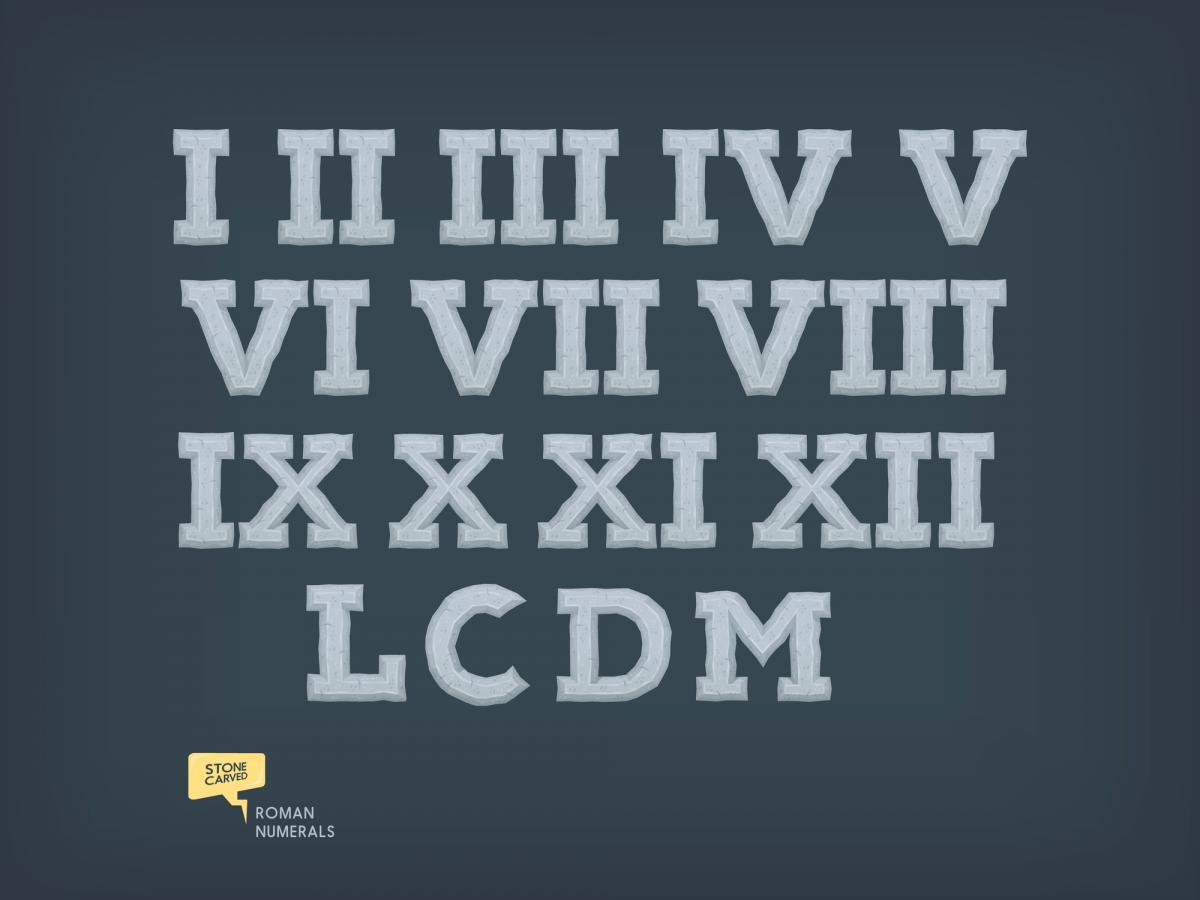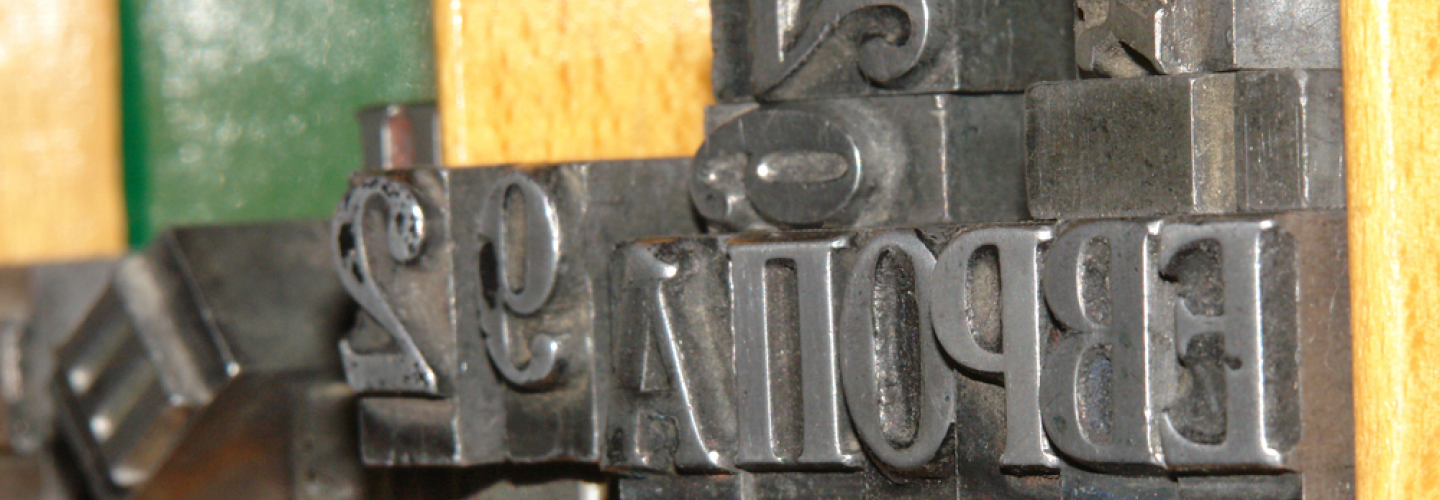
Tipos y características de la tipografía romana
La tipografía romana es una de las más utilizadas y reconocidas en el mundo del diseño gráfico y editorial. Su estructura se caracteriza por la presencia de serifas y por el contraste entre los trazos gruesos y finos, que le permite ser fácilmente legible. Con el paso de los años, han surgido algunas variantes. Todas ellas las conoceremos en detalle en este artículo.
Tipografía romana: principales características
La tipografía romana destaca por su elegancia y legibilidad. Por eso, es tan usada en diseño gráfico y editorial. Su característica principal es la presencia de serifas, que son pequeños trazos que adornan los extremos de las letras. Cuando se trata de un texto largo, son estos los que facilitan la lectura. Pero además, estas serifas le dan un aspecto un tanto clásico y refinado, de ahí que sean habituales en publicaciones como libros, revistas y periódicos.
Otra de sus características más notables es el contraste entre trazos gruesos y finos. Consigue dar dinamismo visual y hace que la lectura se vea facilitada; sobre todo si se trata de tamaños pequeños. Pero también da un aspecto definido y estructurado a las letras.
Como veremos en el siguiente apartado, hay tres grandes categorías dentro de la tipografía romana: antigua, de transición y moderna. La tipografía romana antigua se caracteriza por tener un menor contraste entre los trazos y serifas más redondeadas. Las tipografías de transición tienen mayor contraste y serifas más rectas, mientras que las modernas apuestan por mucho contraste, pero serifas finas que son casi lineales. Todas ellas se suelen usar en textos largos por su claridad y carácter atemporal.
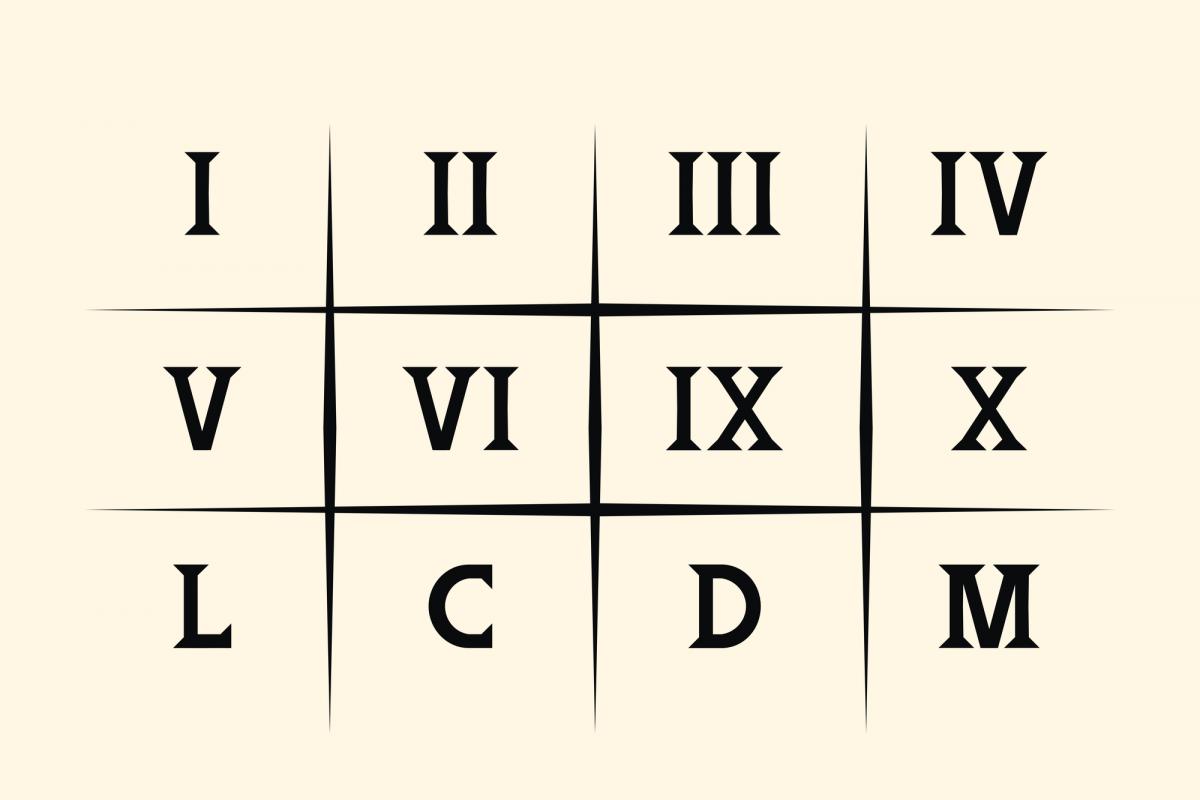
Tipo de letras romana
Si bien ya las hemos mencionado, vamos a conocer en detalle los diferentes tipos de tipografía romana que hay.
Tipografías romanas antiguas
La tipografía romana antigua, también conocida como Garaldas, se distingue por su terminación aguda y por tener una base relativamente ancha. Estas letras presentan trazos variables: los ascendentes suelen ser más finos, mientras que los descendentes son más gruesos. Esta combinación crea un contraste visual muy interesante. Se trata de una característica que además de mejorar la estética, hace lo propio con su legibilidad en diferentes tamaños.
La separación que hay entre los caracteres, que es más grande que la media, es una de las particularidades más notables de las romanas antiguas. Consigue dar sensación de amplitud y claridad. Y en conjunto, estas letras tienen una apariencia sólida en las páginas.
Algunos ejemplos importantes de tipografía romana antigua son Garamond, Trajan, Bembo, Centaur, Minion y Sabon. Todas estas fuentes nos recuerdan a las inscripciones y los números de la Roma Antigua, cuando se grababan en piedra con cinceles. Este vínculo histórico es el responsable de que se use en textos actuales cuando se requiere un toque de elegancia y tradición. En cuanto a sus aplicaciones, son muy frecuentes en libros, documentos formales y en proyectos de diseño que buscan transmitir seriedad.
Romanas de transición
La tipografía romana de transición representa una evolución significativa respecto a la romana antigua. Uno de los cambios más evidentes en esta familia de tipos es la forma de sus serifas. Es este estilo, la terminación es más aguda y estilizada, por lo que transite un aire más contemporáneo.
Aunque los trazos siguen siendo variables, se observa una mayor diferencia entre los finos y los gruesos, en comparación con las romanas antiguas, donde la variación era menos pronunciada. Sin embargo, esta diferencia no es tan extrema como en las tipografías modernas, en las que el contraste es mucho más marcado.
Las letras minúsculas de las tipografías de transición tienden a ser menos angulosas. La redondez está más acentuada y consiguen así una apariencia más armoniosa y agradable a la vista. Este rasgo estilístico facilita la legibilidad, sobre todo en textos de tamaño mediano a grande.
Dentro de las tipografías que pertenecen a esta categoría, encontramos clásicos como Baskerville, la archiconocida Times New Roman y Century Old Style. Estas fuentes destacan por tener una estética equilibrada y porque son muy versátiles a la hora de usarse. Se usan tanto en documentos formales como en libros o revistas. En definitiva, la tipografía romana de transición es una mezcla de elegancia y claridad.